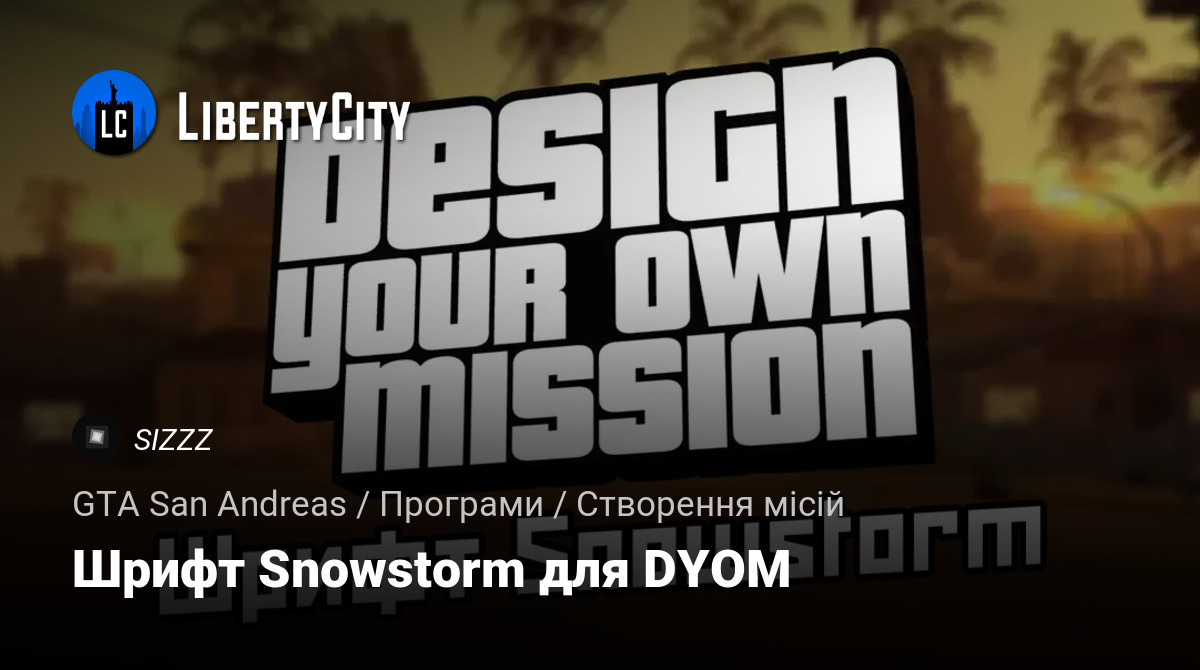
Шрифт Snowstorm для DYOM
Російськомовний шрифт Snowstorm для DYOM. Зроблено на основі шрифту Mefisto 2.0.
Замінено тільки шрифт субтитрів, інші шрифти стандартні. Так само в меню гри збережені англійські шрифти.